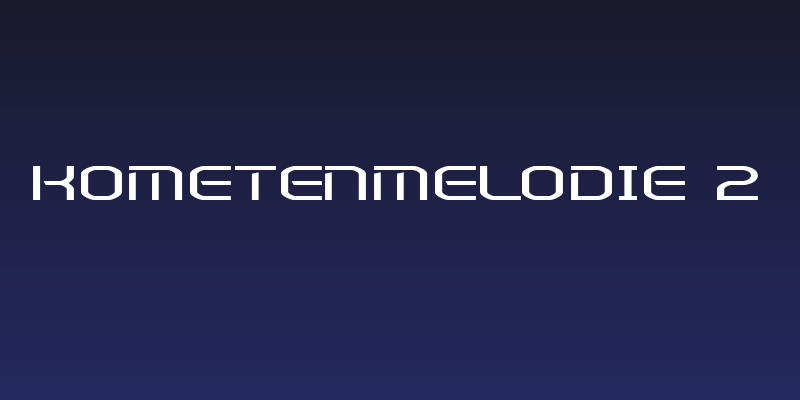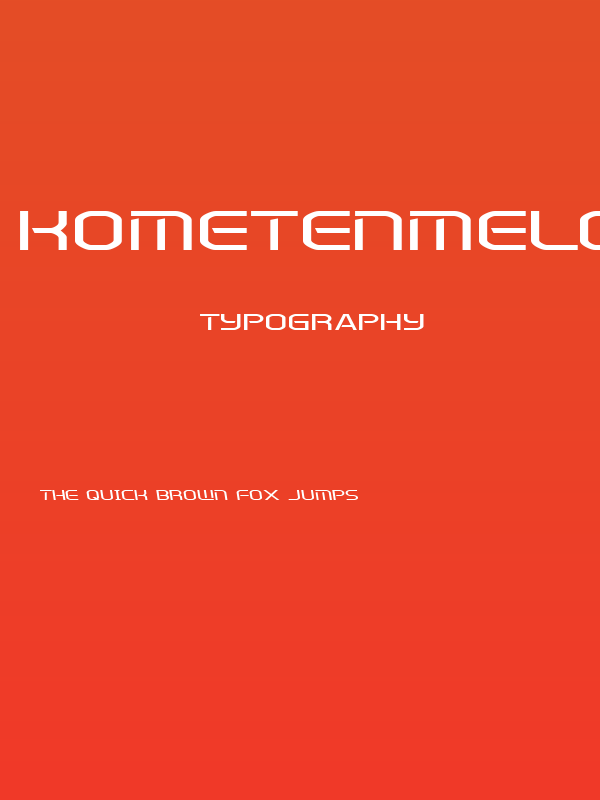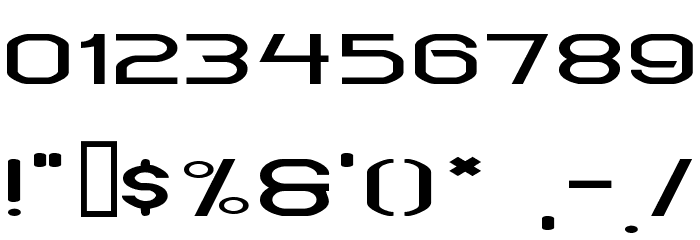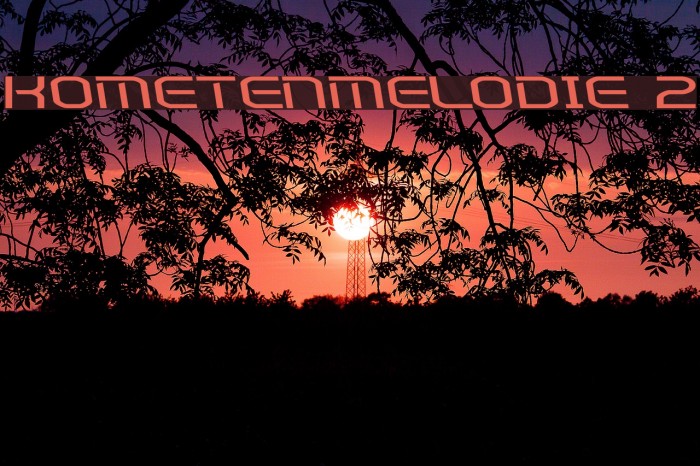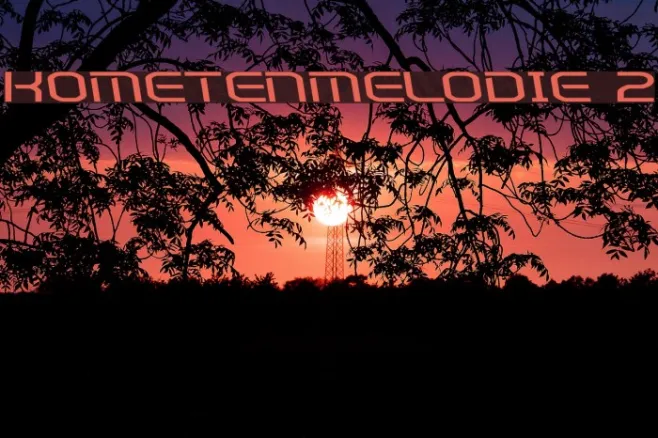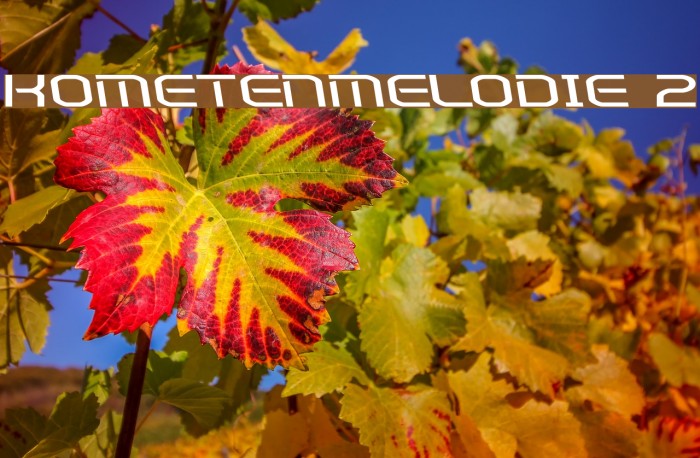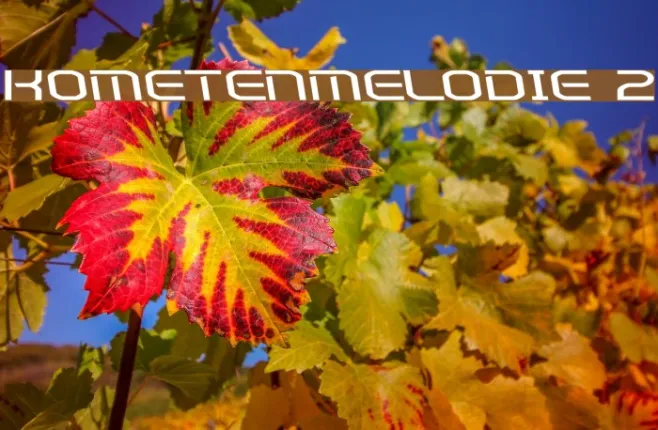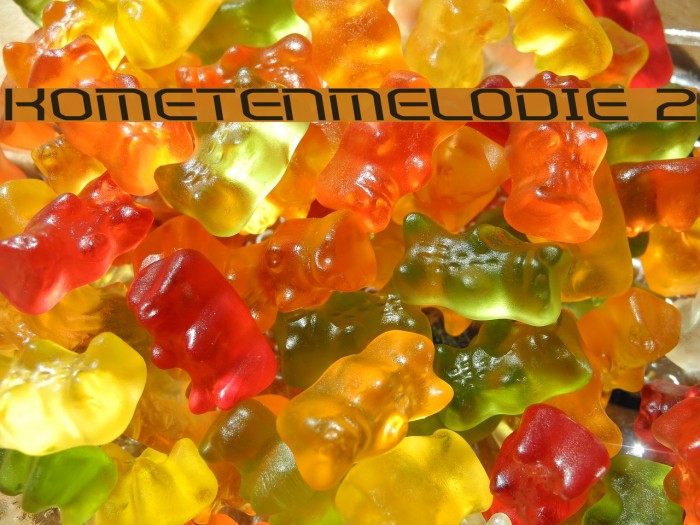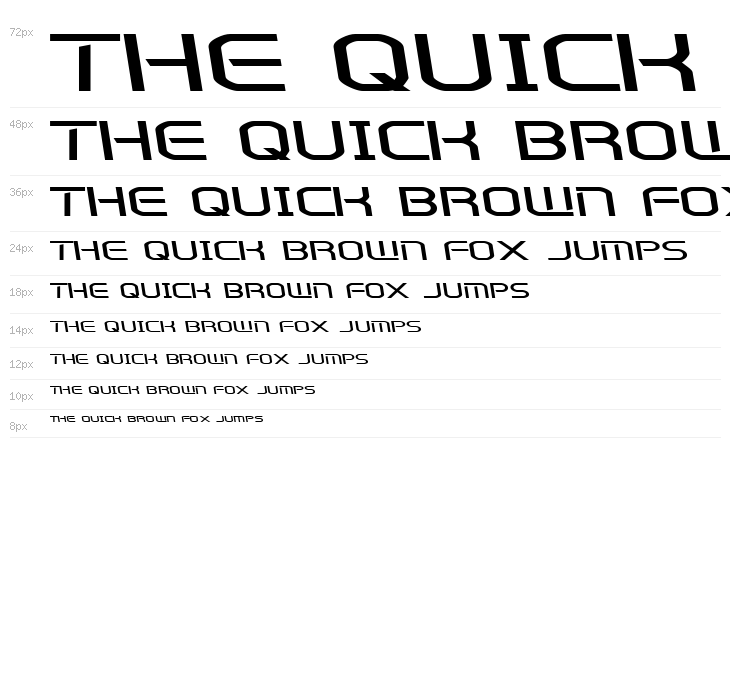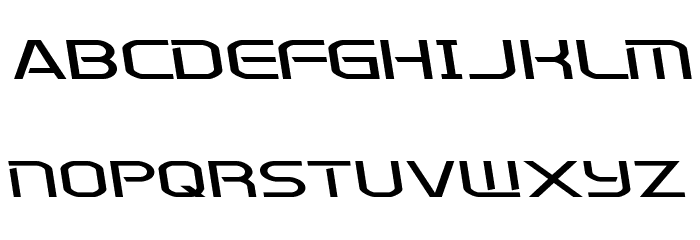
Kometenmelodie 2 Font
| Projets proposés | Ideal for technology branding, sci-fi themed designs, modern advertising, and innovative product packaging. |